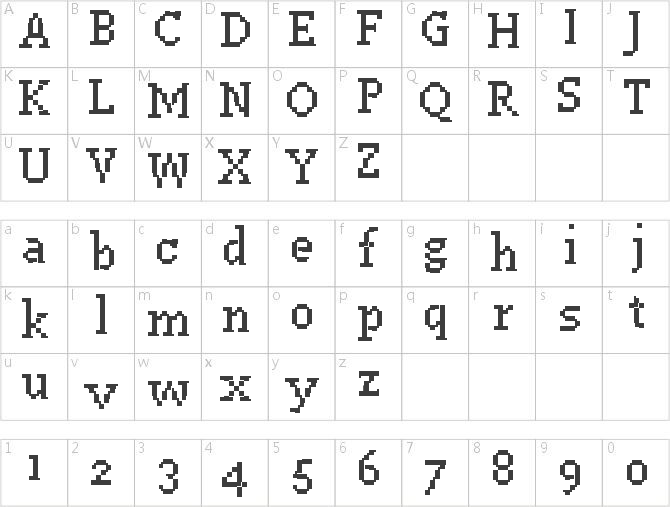
pf_westa_seven_condensed
pf_westa_seven_condensed字體字庫是一款讓人賞心悅目、百看不厭的英文字體,適合各類廣告和產(chǎn)品包裝設(shè)計應(yīng)用,字體大小0.08MB,格式為ttf字體,上傳用戶是wo~,作者/版權(quán)方為未知